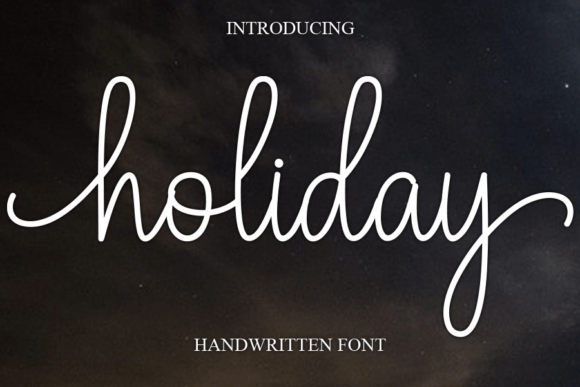
Holiday
Ulasan Font Holiday – Elegância Casual para Segala Desain
Se você procura uma tipografia que combine delicadeza, romantismo e um toque descontraído, o font Holiday é a escolha perfeita. Esta fonte manuscrita, suave e cursiva, destaca-se em projetos que exigem elegância sem perder a leveza, tornando‑se uma ferramenta indispensável para designers que desejam criar peças visualmente impactantes.
- Estilo manuscrito cursivo – oferece um visual autêntico de escrita à mão, ideal para transmitir emoções genuínas.
- Traços suaves e delicados – garantem legibilidade mesmo em tamanhos menores, perfeito para cartões de visita e convites.
- Versatilidade – funciona bem em branding, logotipos, convites de casamento, cartões de felicitação, lookbooks de moda e campanhas de marketing.
- Toque romântico e alegre – adiciona uma sensação de celebração e carinho a qualquer projeto.
Aplicações Ideais
- Identidade visual de marcas que buscam um posicionamento sofisticado e acolhedor.
- Logotipos de empresas de moda, beleza e eventos.
- Convites de casamento, save‑the‑date e cartões de felicitação.
- Campanhas promocionais e peças de marketing que precisam de um visual elegante e casual.
- Lookbooks, catálogos e materiais de branding para boutiques e lojas de roupas.
Por que escolher a Holiday?
A Holiday combina o charme de uma escrita à mão com a modernidade necessária para os designs atuais. Seu estilo único traz um look fancy sem parecer forçado, permitindo que seu público se conecte emocionalmente com a mensagem. Além disso, a fonte está otimizada para uso digital e impressão, garantindo qualidade consistente em qualquer mídia.
Seja para um projeto de casamento, uma campanha publicitária ou a identidade visual de uma marca de moda, a font Holiday entrega o equilíbrio perfeito entre elegância e casualidade. Experimente agora e descubra como esta fonte pode transformar seus designs em verdadeiras obras‑de‑arte que encantam e inspiram.